《死亡笔记》Death Note 原作漫画字体
喜欢《死亡笔记》的朋友们看过来!这里为你盘点了还原原作漫画、书籍封面和电影海报的三个款经典字体。适用动漫同人周边创作、暗黑/悬疑风格海报设计、书籍封面排版、万圣节主题视觉、社交媒体图文分享、视频字幕与封面包装。
Death Note Font 重制版
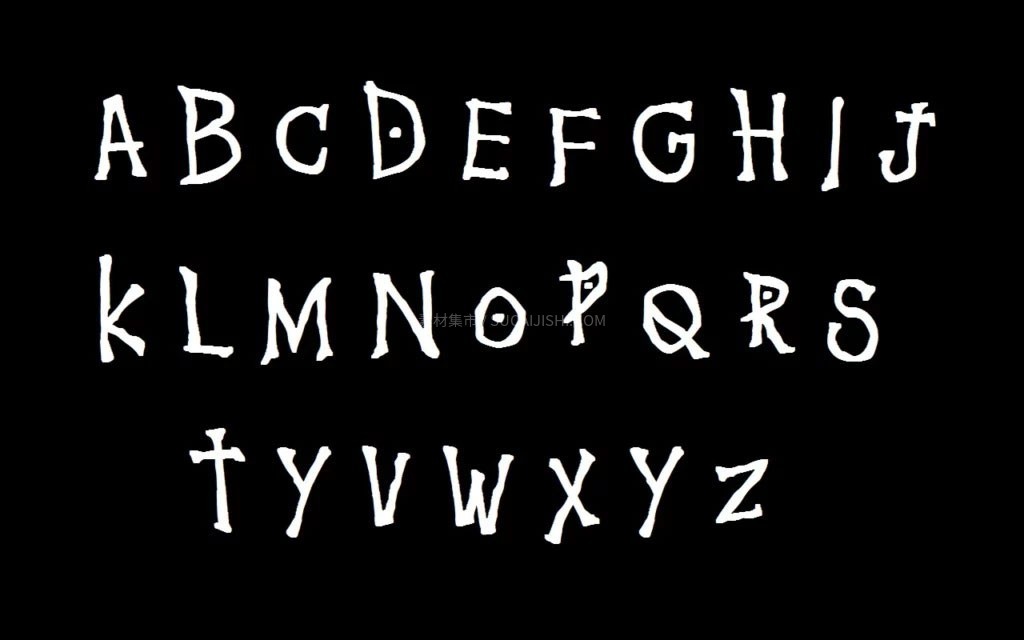
Death
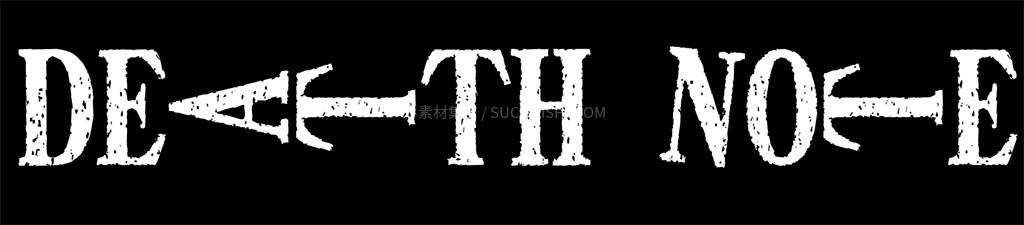
Cloister Black